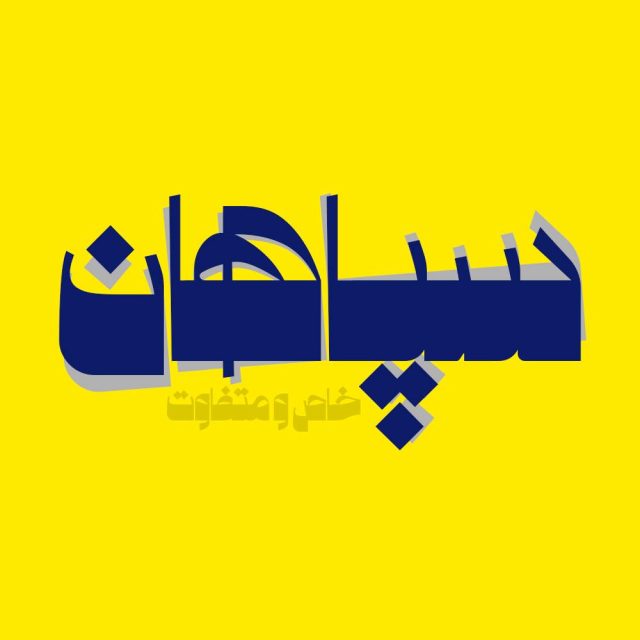
فونت فارسی سپاهان Sepahan Font
فونت فارسی سپاهان یک فونت گرافیکی زیبا و حرفه ای با طراحی مدرن و خاص می باشد که حروف به نرمی و اصولی در کنار یکدیگر…
فونت فارسی سپاهان یک فونت گرافیکی زیبا و حرفه ای با طراحی مدرن و خاص می باشد که حروف به نرمی و اصولی در کنار یکدیگر قرار می گیرند و شکل زیبایی از کلمات را تشکیل می دهند، فونت فارسی سپاهان زیبا و حرفه ای مناسب استفاده در عناوین و تیترها و جملات نسبتا کوتاه و هم طراحی انواع لوگوتایپ، تکست گرافی و استفاده در طراحی های خاص می باشد.
• مناسب طراحی بسته بندی ها و چاپ
• فونت ویژه تبلیغات محیطی
• فونت طراحی کاور اینستاگرام
• فونت حرفه ای برای تولید محتوا
• فونت فارسی طراحی وبسایت
• فونت طراحی لوگو تایپ فارسی
• مناسب استفاده در تابلو های چلنیوم و طراحی حروف
پیشنمایش و نمونه تایپ های فونت سپاهان